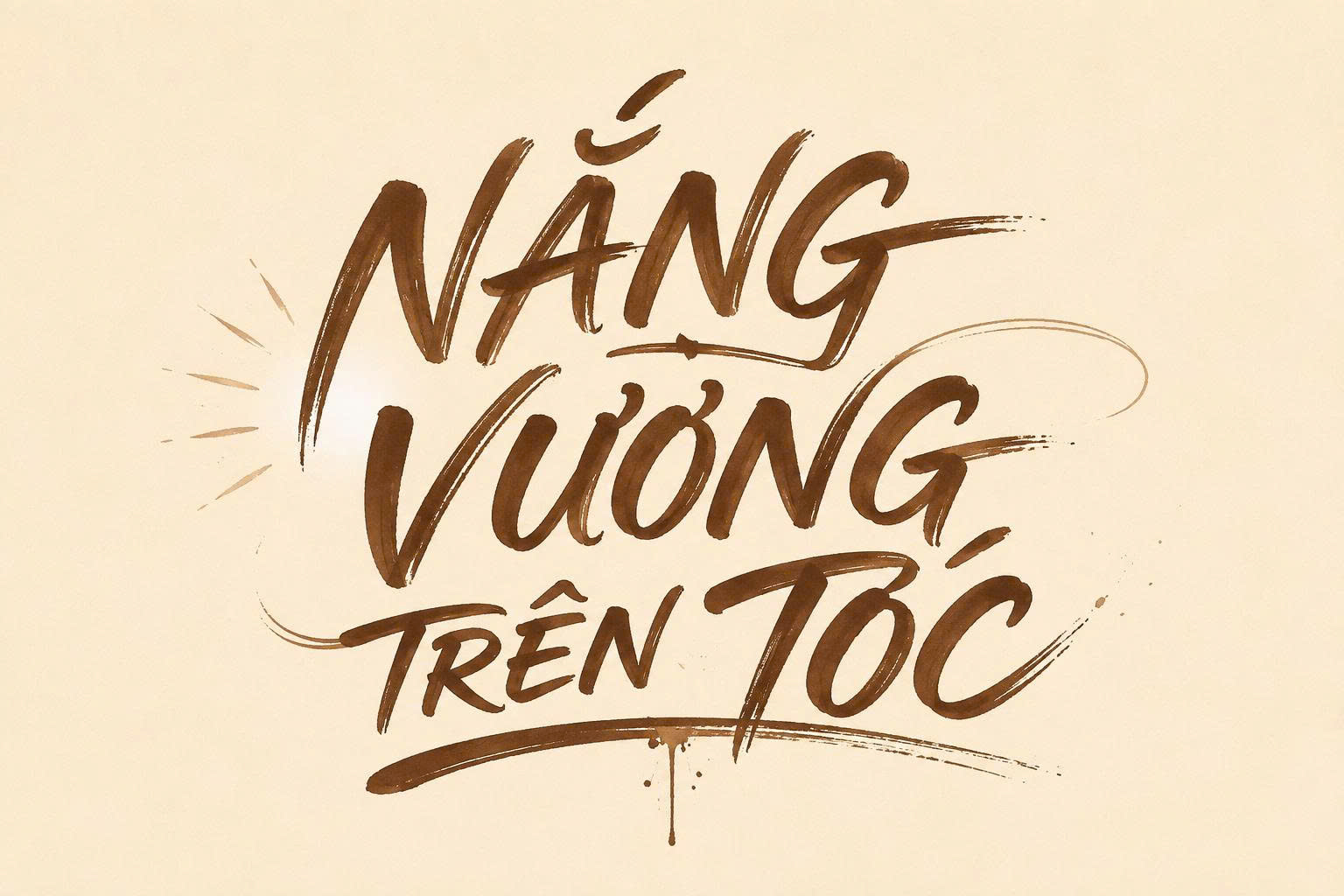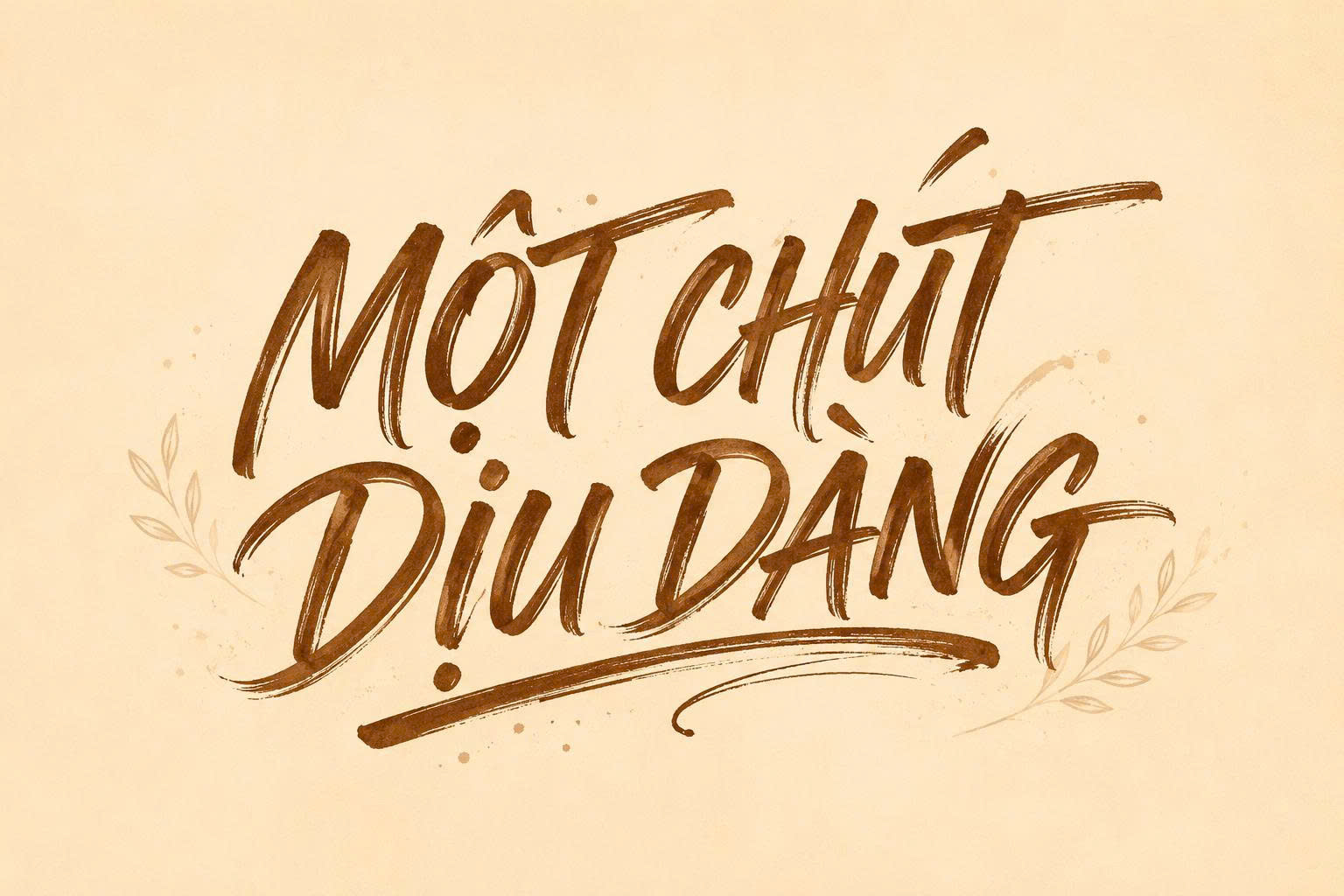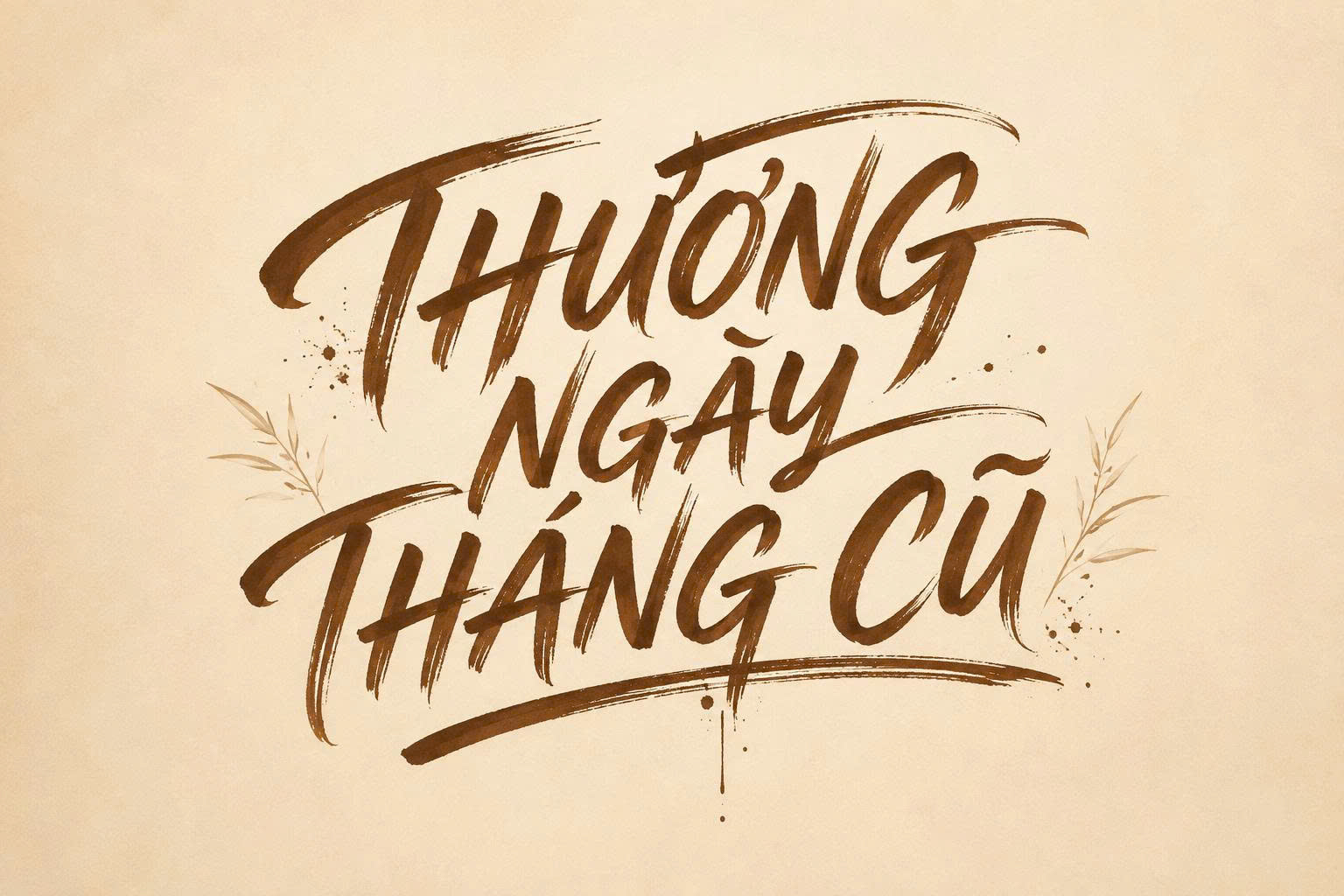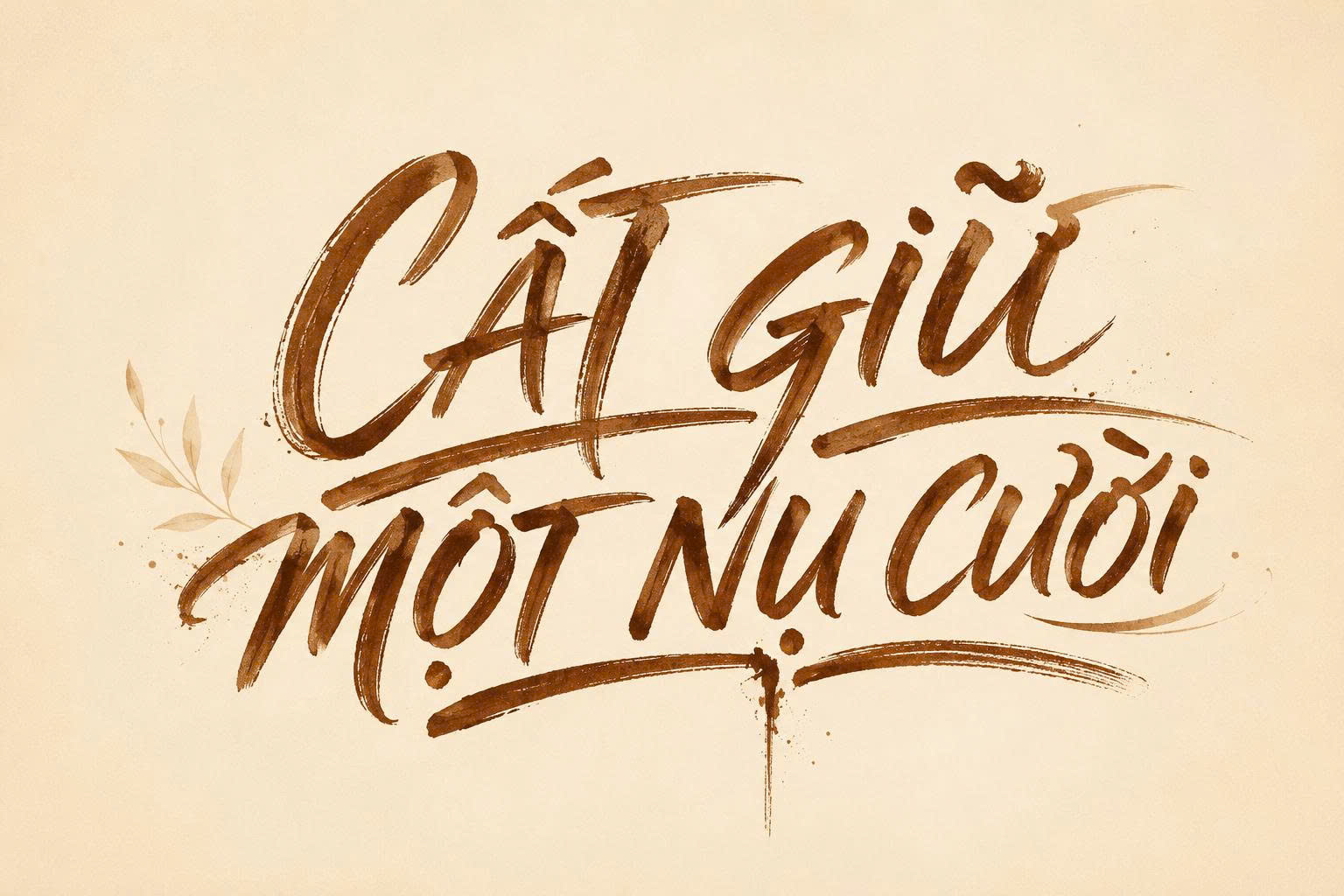
Font brush Việt hóa là dòng phông chữ mô phỏng lại những nhát bút lông hoặc cọ mực đầy ngẫu hứng, mang đến vẻ đẹp phóng khoáng, tự nhiên và đậm chất nghệ thuật cho các bản thiết kế. Khác với các dòng font chân phương, font chữ brush Việt hóa giúp designer truyền tải cảm xúc mạnh mẽ thông qua các nét xước và độ thanh đậm biến thiên linh hoạt. Doozypack.vn chia sẻ bộ sưu tập font chữ nét cọ Việt hóa trọn bộ, hỗ trợ đầy đủ bảng mã tiếng Việt để bạn tự do sáng tạo bao bì, logo hay poster mà không lo lỗi hiển thị dấu thanh.
Font chữ brush Việt hóa là gì? Tại sao nên sử dụng trong thiết kế?
Font brush (hay còn gọi là font nét cọ) là sự kết hợp giữa kỹ thuật đồ họa và phong cách thư pháp hiện đại. Việc sử dụng dòng font này đang trở thành xu hướng nhờ những ưu điểm vượt trội về mặt thị giác.
Mẫu chữ viết tay bằng nét cọ với đường nét xước tự nhiên
Đặc điểm của font chữ nét cọ Việt hóa
Đặc trưng lớn nhất của dòng font này là các đường nét có cấu trúc “xước” hoặc mực loang không đồng đều, mô phỏng chân thực quy trình vẽ tay bằng cọ thực tế. Các ký tự thường có độ cao thấp khác nhau, tạo nên nhịp điệu chuyển động sinh động cho dòng văn bản. Khi được Việt hóa, các bộ dấu (sắc, huyền, hỏi, ngã, nặng) được tinh chỉnh để hài hòa với độ dày của nét cọ, giúp tổng thể bản thiết kế trở nên nhất quán và chỉn chu.
Mang lại cá tính và sự phóng khoáng cho thương hiệu
Nếu bạn muốn thương hiệu của mình thoát khỏi vẻ khô cứng, font brush Việt hóa chính là giải pháp. Nó mang lại cảm giác thủ công (handmade), gần gũi nhưng vẫn rất hiện đại. Dòng font này đặc biệt hiệu quả khi dùng làm tiêu đề cho các sản phẩm ngành thực phẩm, mỹ phẩm thiên nhiên, thời trang dạo phố hoặc các sự kiện sáng tạo dành cho giới trẻ.
Thiết kế poster phong cách viết tay với chữ nét cọ nổi bật
03 Ứng dụng của font brush trong thiết kế bao bì và in ấn tại Doozypack.vn
Tại Doozypack.vn, chúng tôi thấy rằng các dòng font chữ brush Việt hóa luôn tạo ra sức hút đặc biệt khi xuất hiện trên thành phẩm bao bì:
• Hộp giấy quà tặng: Tên thương hiệu in bằng font brush trên nền giấy Ivory cán mờ mang lại cảm giác sản phẩm cao cấp, có cá tính riêng.
• Túi giấy thời trang: Những câu slogan ngắn in theo phong cách nét cọ giúp chiếc túi giấy trở nên sành điệu và thu hút sự chú ý của khách hàng.
• Tem nhãn sản phẩm: Phù hợp cho các dòng sản phẩm “Organic”, thực phẩm handmade hoặc đồ uống giải khát, nhấn mạnh tính tự nhiên và quy trình làm tay tỉ mỉ.
Mẫu bao bì sản phẩm sử dụng kiểu chữ viết tay nghệ thuật
03 lưu ý kỹ thuật khi in ấn font chữ brush
Việc đưa một bộ font có cấu trúc phức tạp như nét cọ lên bao bì giấy đòi hỏi designer cần am hiểu kỹ thuật in ấn thực tế tại Doozypack.vn:
• Xử lý nét xước khi ép kim: Các font brush thường có những mảnh xước mực rất nhỏ. Khi gia công ép kim (Hot Stamping), những chi tiết li ti này dễ bị bong tróc hoặc không bám kim đều. Bạn nên “dọn” bớt các nét xước quá vụn trước khi làm khuôn ép.
• Hạn chế bết mực trên giấy Kraft: Giấy Kraft có độ thấm mực cao. Với những font brush có nét chữ quá đậm và sát nhau, mực có thể bị lan nhòe (dot gain) làm mất đi vẻ đẹp của nét cọ. Hãy tăng nhẹ khoảng cách chữ (Tracking) để bản in được thông thoáng.
• Luôn Convert Font: Trước khi gửi file in đến Doozypack.vn, hãy luôn thực hiện lệnh Create Outlines để đảm bảo nội dung không bị lỗi font hoặc mất dấu khi mở trên các máy in chuyên dụng.
Hướng dẫn tải mẫu chữ nhanh chóng
5. Doozypack.vn có hỗ trợ thiết kế bao bì bằng font brush không?